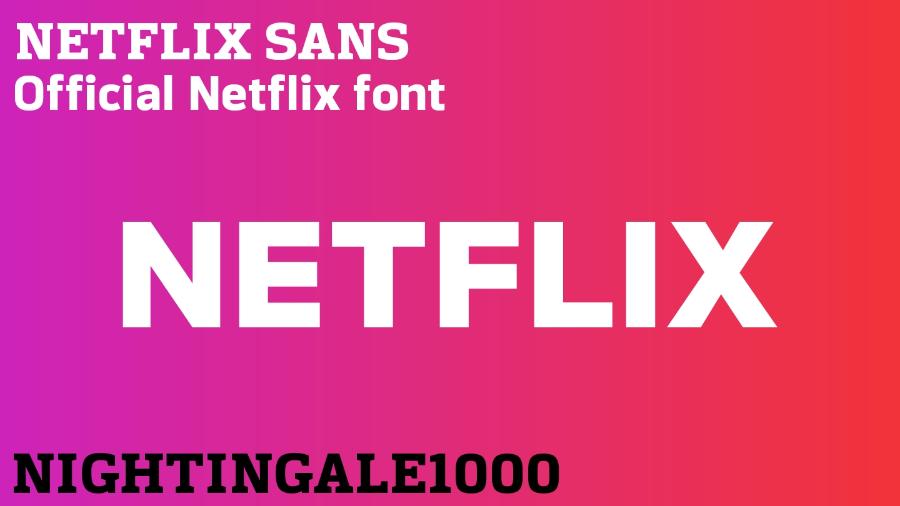
12 Doanh Nghiệp Tối Ưu Chi Phí Hàng Triệu USD Nhờ Đầu Tư Vào Typeface Độc Quyền
Khám phá cách 12 công ty nổi tiếng tiết kiệm hàng triệu USD mỗi năm nhờ sở hữu font chữ (typeface) riêng. Tìm hiểu tầm quan trọng của việc đầu tư vào thiết kế typography độc đáo và sự khác biệt mà nó mang lại cho các thương hiệu.
Việc sở hữu một typeface riêng có thể mang lại cho các công ty một lợi thế cạnh tranh lớn và giúp tiết kiệm hàng triệu USD mỗi năm. Các thương hiệu lớn như Google, Netflix, và Airbnb đã chứng minh rằng một font chữ độc quyền không chỉ giúp xây dựng thương hiệu mà còn tạo ra hiệu quả tài chính vượt trội. Bài viết dưới đây sadesign sẽ giới thiệu cách thức các công ty này tiết kiệm chi phí và tối ưu hóa quy trình thiết kế nhờ việc sở hữu typeface riêng.
1. Giới Thiệu Về Typeface Và Tầm Quan Trọng Của Nó
Trong thế giới thiết kế đồ họa và truyền thông, "typeface" hay còn gọi là font chữ, là một trong những yếu tố không thể thiếu trong việc xây dựng thương hiệu. Một typeface được thiết kế riêng biệt không chỉ giúp tạo nên sự khác biệt mà còn có thể tiết kiệm chi phí dài hạn cho các công ty. Hầu hết các công ty lớn đều nhận thấy rằng việc sử dụng các font chữ thương mại hoặc miễn phí từ các nhà cung cấp bên thứ ba sẽ phải trả các khoản chi phí bản quyền, đặc biệt khi sử dụng font chữ này trên nhiều nền tảng khác nhau.
Điều này có thể dẫn đến chi phí phát sinh mỗi năm mà các công ty không thể kiểm soát được. Vì vậy, sở hữu một typeface riêng biệt là một chiến lược kinh doanh thông minh, giúp công ty không chỉ giảm thiểu chi phí mà còn nâng cao giá trị thương hiệu. Trong phần tiếp theo, chúng ta sẽ đi sâu vào cách các công ty đã tiết kiệm được hàng triệu USD từ việc sở hữu typeface riêng.
2. Top 12 Công Ty Tiết Kiệm Hàng Triệu USD Nhờ Sở Hữu Typeface Riêng
Việc sở hữu typeface riêng không chỉ giúp các công ty xây dựng bản sắc thương hiệu độc đáo mà còn mang lại lợi ích kinh tế đáng kể. Theo thống kê, nhiều doanh nghiệp lớn đã tiết kiệm hàng triệu USD nhờ việc giảm thiểu chi phí bản quyền phông chữ từ bên thứ ba và tối ưu hóa hiệu quả truyền thông. Trong số đó, 12 công ty hàng đầu đã áp dụng chiến lược này thành công, biến typeface thành một phần cốt lõi trong chiến lược thương hiệu, đồng thời tạo ra sự khác biệt rõ rệt trên thị trường cạnh tranh.
2.1. Google – Roboto: Chuyển Mình Trong Từng Chi Tiết
Kể từ khi ra mắt, Google đã khẳng định vị thế dẫn đầu trong ngành công nghệ thông qua những đổi mới không ngừng. Một trong những sáng tạo đáng chú ý của Google là font chữ Roboto, được thiết kế riêng cho hệ điều hành Android. Việc sử dụng Roboto không chỉ giúp Google tiết kiệm chi phí bản quyền mà còn tạo ra một sự đồng nhất về mặt thẩm mỹ trên mọi thiết bị Android.
Roboto là một trong những typeface phổ biến nhất trên thế giới, và có thể nói rằng việc sở hữu font chữ này đã giúp Google tiết kiệm hàng triệu USD chi phí bản quyền hàng năm cho việc sử dụng font trên các nền tảng, ứng dụng và dịch vụ của mình.
Google đã chứng minh sự quan trọng của việc sở hữu typeface riêng khi phát triển Roboto, một font chữ mang tính biểu tượng giúp công ty không chỉ củng cố nhận diện thương hiệu mà còn tiết kiệm hàng triệu USD chi phí bản quyền. Roboto không chỉ thể hiện sự tinh tế trong thiết kế mà còn tối ưu hóa trải nghiệm người dùng trên các nền tảng của Google. Việc chuyển mình trong từng chi tiết nhỏ của typeface này đã giúp Google duy trì sự nhất quán và chuyên nghiệp, đồng thời khẳng định vị thế dẫn đầu trong ngành công nghệ.
2.2. Airbnb – Cải Tiến Typography Để Tăng Cường Nhận Diện Thương Hiệu
Airbnb là một trong những công ty điển hình sử dụng typeface riêng để tăng cường sự khác biệt và tiết kiệm chi phí. Thay vì sử dụng các font chữ sẵn có, Airbnb đã phát triển một font chữ mang tên Airbnb Cereal. Việc sở hữu font chữ riêng giúp Airbnb không phải chi trả cho việc mua bản quyền và đồng thời tạo ra một phong cách thiết kế độc đáo, dễ nhận diện trên mọi nền tảng truyền thông.
Sở hữu Airbnb Cereal đã giúp công ty này giảm bớt sự phụ thuộc vào các dịch vụ bên ngoài, đồng thời kiểm soát được chất lượng và tính nhất quán trong việc sử dụng typography trên toàn cầu.
Việc cải tiến typography không chỉ giúp tối ưu hóa chi phí liên quan đến bản quyền phông chữ mà còn tạo nên sự đồng nhất và độc đáo trong các tài liệu truyền thông, giao diện người dùng và chiến dịch quảng bá. Đây là một chiến lược thông minh, thể hiện tầm nhìn dài hạn của Airbnb trong việc xây dựng thương hiệu mạnh mẽ và bền vững trên thị trường toàn cầu.
2.3. Netflix – Netflix Sans: Đơn Giản Nhưng Ấn Tượng
Netflix là một ví dụ điển hình về việc sử dụng font chữ riêng để tối ưu hóa chi phí. Công ty đã phát triển một typeface mang tên Netflix Sans, với mục tiêu giảm thiểu chi phí bản quyền từ việc sử dụng các font thương mại. Netflix Sans được thiết kế để phù hợp với phong cách tối giản của Netflix, đồng thời dễ đọc và dễ nhìn trên các thiết bị và nền tảng khác nhau.
Với việc sử dụng Netflix Sans, Netflix không chỉ tiết kiệm được hàng triệu USD mà còn thể hiện được sự sáng tạo và cam kết trong việc xây dựng thương hiệu mạnh mẽ. Sự thống nhất trong typography là yếu tố quan trọng giúp Netflix duy trì sự nhận diện thương hiệu trên toàn cầu.
Với thiết kế đơn giản nhưng tinh tế, Netflix Sans thể hiện sự hiện đại và sáng tạo, đồng thời phù hợp với chiến lược truyền thông của công ty. Đây là một ví dụ điển hình cho việc đầu tư vào typeface tùy chỉnh có thể mang lại giá trị lâu dài cả về mặt tài chính lẫn thương hiệu.
2.4. Apple – San Francisco: Sự Hoàn Hảo Trong Thiết Kế
Apple luôn chú trọng đến sự hoàn hảo trong từng chi tiết thiết kế, và font chữ San Francisco là minh chứng rõ rệt cho điều đó. Được sử dụng trên tất cả các thiết bị của Apple, từ iPhone đến iMac, San Francisco không chỉ giúp tiết kiệm chi phí bản quyền mà còn giúp Apple tạo ra sự nhất quán trong trải nghiệm người dùng.
San Francisco là một trong những typeface đặc biệt khi có khả năng thay đổi kích thước và hiển thị một cách rõ ràng và dễ đọc trên các thiết bị của Apple. Việc sở hữu San Francisco đã giúp Apple tiết kiệm đáng kể chi phí liên quan đến việc sử dụng font chữ bên ngoài.
2.5. Spotify – Spotify Circular: Đơn Giản Nhưng Hiện Đại
Spotify Circular là một ví dụ điển hình về việc sử dụng font chữ riêng để tiết kiệm chi phí và đồng thời nâng cao giá trị thương hiệu. Font chữ này được Spotify sử dụng trên mọi nền tảng của mình, từ ứng dụng di động đến website, mang lại sự đồng nhất trong thiết kế.
Với Spotify Circular, Spotify không chỉ tối ưu hóa chi phí mà còn xây dựng được một diện mạo đơn giản nhưng vô cùng hiện đại, dễ nhận diện và dễ dàng tiếp cận người dùng ở mọi nơi. Typeface này được thiết kế với phong cách đơn giản nhưng hiện đại, không chỉ giúp thương hiệu tạo dấu ấn riêng biệt mà còn tối ưu hóa chi phí liên quan đến việc cấp phép sử dụng phông chữ từ bên thứ ba. Đây là một minh chứng rõ ràng cho tầm quan trọng của việc đầu tư vào bản sắc thương hiệu thông qua thiết kế sáng tạo, đồng thời thể hiện sự chuyên nghiệp và chiến lược dài hạn trong quản lý tài chính và hình ảnh doanh nghiệp.
2.6. The New York Times – NYT Franklin: Đặc Sắc Và Độc Đáo
Tờ báo The New York Times là một trong những thương hiệu có ảnh hưởng lớn trong ngành truyền thông. Việc phát triển và sở hữu font chữ NYT Franklin giúp tờ báo này tiết kiệm hàng triệu USD chi phí bản quyền và đồng thời tạo ra sự thống nhất trong mọi ấn phẩm, từ báo in cho đến website và các nền tảng kỹ thuật số.
NYT Franklin được thiết kế để dễ đọc và dễ sử dụng, đảm bảo người đọc có thể tiếp cận thông tin một cách nhanh chóng và dễ dàng. Việc sở hữu font chữ này giúp The New York Times duy trì được sự chuyên nghiệp và đẳng cấp trong thiết kế, đồng thời tiết kiệm chi phí lâu dài.
Typeface này không chỉ thể hiện sự chuyên nghiệp và độc đáo trong phong cách thiết kế của tờ báo, mà còn giúp tổ chức tiết kiệm hàng triệu USD chi phí bản quyền phông chữ. Đây là một ví dụ điển hình về việc đầu tư vào bản sắc thương hiệu thông qua thiết kế, đồng thời tối ưu hóa hiệu quả tài chính và duy trì tính nhận diện độc quyền trên toàn cầu.
2.7. Microsoft – Segoe: Một Font Chữ Toàn Diện
Microsoft đã sử dụng font chữ Segoe trong nhiều năm, từ các sản phẩm phần mềm đến hệ điều hành Windows. Segoe không chỉ giúp Microsoft tiết kiệm chi phí bản quyền mà còn tạo ra một diện mạo đồng nhất cho các sản phẩm của công ty.
Sở hữu Segoe đã giúp Microsoft xây dựng thương hiệu mạnh mẽ và thống nhất, đồng thời tiết kiệm được một khoản chi phí lớn mỗi năm. Đây là một font chữ toàn diện, được thiết kế để tối ưu hóa trải nghiệm người dùng trên các nền tảng và sản phẩm của Microsoft. Segoe không chỉ góp phần nâng cao tính nhận diện thương hiệu mà còn giúp cải thiện hiệu suất hiển thị, giảm chi phí bản quyền liên quan đến việc sử dụng các font chữ bên ngoài. Việc đầu tư vào typeface riêng như Segoe không chỉ thể hiện tầm nhìn chiến lược của Microsoft mà còn là minh chứng cho sự quan trọng của thiết kế trong việc xây dựng và duy trì thương hiệu mạnh mẽ.
2.8 IBM
• Lịch sử: IBM, hay International Business Machines Corporation, là một biểu tượng của ngành công nghệ. Với hơn một thế kỷ lịch sử, IBM đã không ngừng đổi mới và định hình lại thế giới công nghệ thông tin.
• Typeface riêng: IBM Plex:
• Được ra mắt vào năm 2017, IBM Plex là một typeface mã nguồn mở, thể hiện cam kết của IBM đối với sự minh bạch và hợp tác.
• Thiết kế của IBM Plex mang đậm tính hiện đại, rõ ràng và dễ đọc, phù hợp với mọi ứng dụng từ in ấn đến kỹ thuật số.
• Tính linh hoạt của IBM Plex giúp đảm bảo sự nhất quán trên tất cả các sản phẩm và dịch vụ của IBM, từ phần mềm đến phần cứng.
• Giúp IBM tiết kiệm chi phí bản quyền font chữ trên quy mô toàn cầu.
• Lợi ích:
• Việc sở hữu IBM Plex giúp IBM tiết kiệm hàng triệu đô la chi phí bản quyền font chữ, đặc biệt là khi áp dụng trên hàng triệu sản phẩm và tài liệu.
• IBM Plex củng cố hình ảnh thương hiệu của IBM là một công ty công nghệ tiên tiến, đáng tin cậy và có trách nhiệm.
• Việc sử dụng một typeface đồng nhất giúp tạo ra trải nghiệm người dùng liền mạch và chuyên nghiệp.
2.9. YouTube
• Lịch sử: YouTube là nền tảng chia sẻ video lớn nhất thế giới, nơi mọi người có thể tìm thấy và chia sẻ nội dung video từ khắp nơi trên thế giới.
• Typeface riêng: YouTube Sans:
• YouTube Sans được thiết kế để phản ánh tính năng động, sáng tạo và toàn cầu của YouTube.
• Font chữ này có tính dễ đọc cao, phù hợp với nhiều ngôn ngữ và thiết bị khác nhau.
• YouTube Sans giúp tạo ra một bản sắc thương hiệu mạnh mẽ và nhất quán trên toàn bộ nền tảng YouTube.
• Lợi ích:
• YouTube Sans giúp củng cố hình ảnh thương hiệu của YouTube là một nền tảng video năng động, sáng tạo và đa dạng.
• Việc sử dụng một typeface đồng nhất giúp tạo ra trải nghiệm người dùng liền mạch và chuyên nghiệp.
• Tiết kiệm chi phí bản quyền font chữ.
2.10. BBC
• Lịch sử: BBC là một trong những đài truyền hình và phát thanh công cộng uy tín nhất thế giới, nổi tiếng với các chương trình tin tức và giải trí chất lượng cao.
• Typeface riêng: BBC Reith:
• BBC Reith được thiết kế để tối ưu hóa khả năng đọc trên nhiều nền tảng khác nhau, từ TV, radio đến web và thiết bị di động.
• Font chữ này có tính trung lập và chuyên nghiệp cao, phản ánh sự tin cậy và khách quan của BBC.
• BBC Reith giúp củng cố hình ảnh thương hiệu của BBC là một đài truyền thông đáng tin cậy và chuyên nghiệp.
• Lợi ích:
• BBC Reith giúp tăng cường sự tin cậy và chuyên nghiệp của thương hiệu BBC.
• Font chữ này giúp cải thiện trải nghiệm người dùng bằng cách tăng cường khả năng đọc trên tất cả các nền tảng.
• Tiết kiệm chi phí bản quyền.
2.11. Medium
• Lịch sử: Medium là một nền tảng xuất bản trực tuyến phổ biến, nơi các nhà văn và người đọc có thể chia sẻ và khám phá những ý tưởng.
• Typeface riêng: Charter và Whitney:
• Medium sử dụng hai typeface, Charter và Whitney, để tạo ra một trải nghiệm đọc dễ chịu và thoải mái.
• Cả hai font chữ này đều có tính dễ đọc cao và phù hợp với màn hình kỹ thuật số.
• Lợi ích:
• Charter và Whitney giúp tối ưu hóa trải nghiệm đọc cho người dùng Medium.
• Hai font chữ này giúp tăng cường tính chuyên nghiệp và đáng tin cậy của nền tảng Medium.
2.12. Shopify
• Lịch sử: Shopify là một nền tảng thương mại điện tử hàng đầu, giúp các doanh nghiệp xây dựng và phát triển cửa hàng trực tuyến.
• Typeface riêng: Shopify Sans:
• Shopify Sans được thiết kế để phản ánh tính hiện đại, thân thiện với người dùng và đáng tin cậy của nền tảng Shopify.
• Font chữ này giúp tạo ra một bản sắc thương hiệu mạnh mẽ và nhất quán trên tất cả các kênh truyền thông của Shopify.
• Lợi ích:
• Shopify Sans giúp tăng cường sự nhận diện thương hiệu của Shopify trong lĩnh vực thương mại điện tử.
• Font chữ này giúp cải thiện trải nghiệm người dùng bằng cách tạo ra một giao diện thân thiện và chuyên nghiệp.
3. Lợi Ích Khi Sở Hữu Typeface Riêng
Việc sở hữu một typeface riêng mang lại nhiều lợi ích cho các công ty, bao gồm:
• Tiết kiệm chi phí dài hạn: Việc sở hữu typeface riêng không chỉ mang lại giá trị nhận diện thương hiệu độc đáo mà còn giúp các doanh nghiệp tiết kiệm chi phí đáng kể. Theo thống kê, nhiều công ty lớn trên thế giới đã tiết kiệm hàng triệu USD nhờ việc sử dụng typeface độc quyền, thay vì phải trả phí bản quyền cho các font chữ thương mại. Bạn không phải trả tiền bản quyền hàng năm cho các font chữ bên ngoài.
• Tăng cường nhận diện thương hiệu: Một typeface riêng giúp tạo sự khác biệt và dễ dàng nhận diện thương hiệu trên toàn cầu. Typeface độc quyền giúp thương hiệu dễ dàng ghi dấu ấn trong tâm trí khách hàng thông qua sự nhất quán và độc đáo trong thiết kế. Ngoài ra, việc sử dụng typeface riêng còn thể hiện tính chuyên nghiệp và cam kết đầu tư vào hình ảnh thương hiệu lâu dài.
• Tối ưu hóa trải nghiệm người dùng: Typeface riêng có thể được thiết kế sao cho phù hợp với sản phẩm và người dùng của công ty. Đây là một chiến lược dài hạn thông minh mà các doanh nghiệp nên cân nhắc để vừa tối ưu hóa ngân sách, vừa khẳng định dấu ấn riêng trên thị trường cạnh tranh.
• Kiểm soát thiết kế: Công ty có thể hoàn toàn kiểm soát cách thức sử dụng và phát triển typeface theo nhu cầu của mình.
4. Kết Luận
Việc sở hữu một typeface riêng không chỉ mang lại lợi ích về mặt thẩm mỹ mà còn giúp các công ty tiết kiệm hàng triệu USD chi phí bản quyền hàng năm. Những công ty lớn như Google, Airbnb, Netflix, Apple, và nhiều thương hiệu khác đã chứng minh rằng đầu tư vào font chữ riêng biệt là một chiến lược lâu dài, giúp tiết kiệm chi phí và tăng cường sự nhận diện thương hiệu. Khi một công ty quyết định sở hữu một typeface riêng, họ không chỉ giảm thiểu chi phí mà còn xây dựng được một phong cách thiết kế độc đáo và dễ dàng thu hút người tiêu dùng.